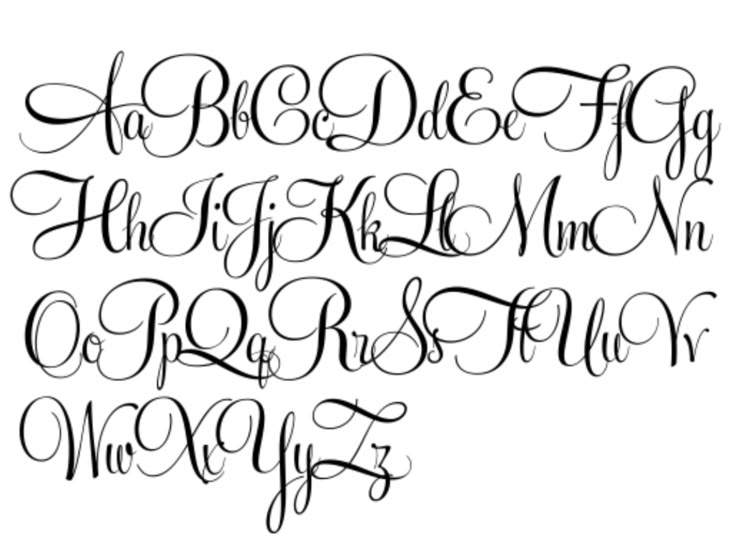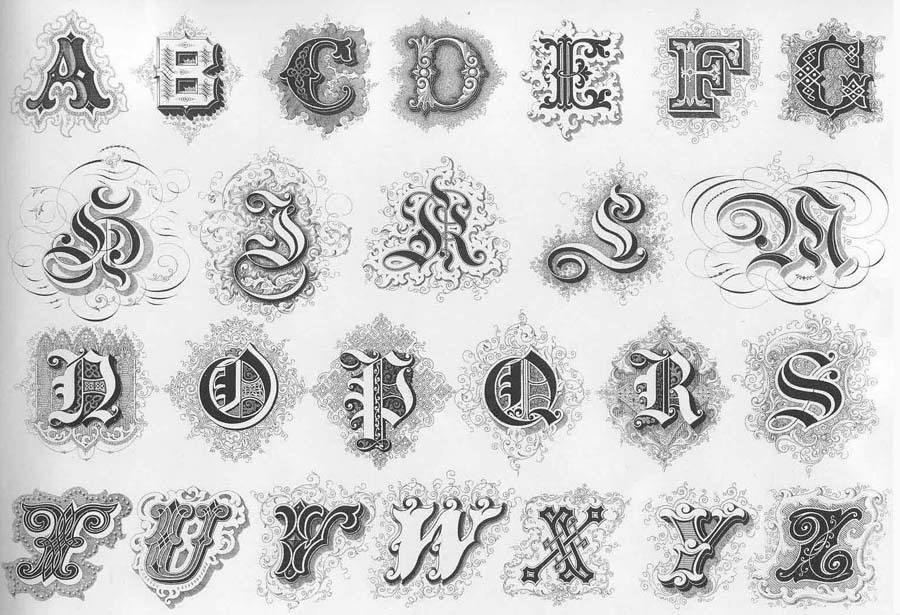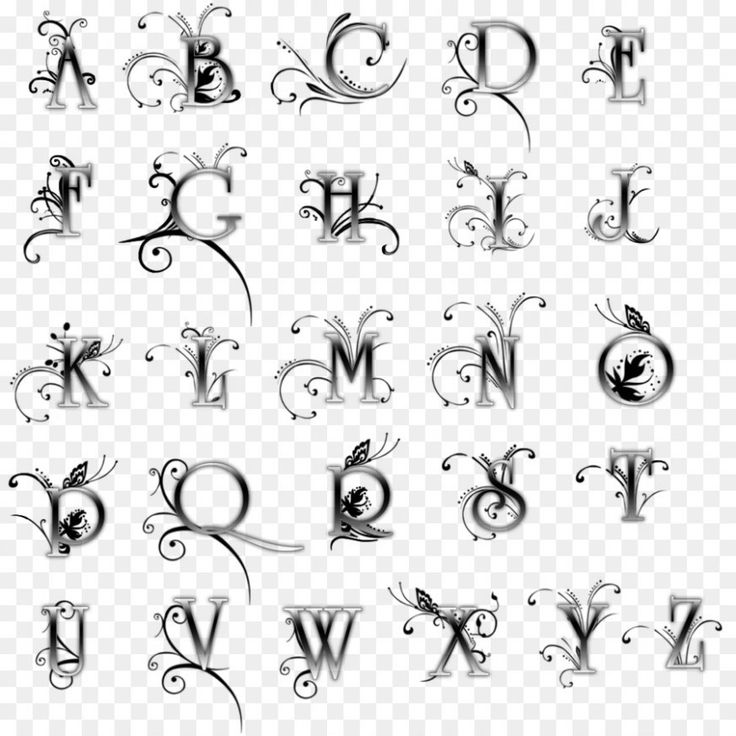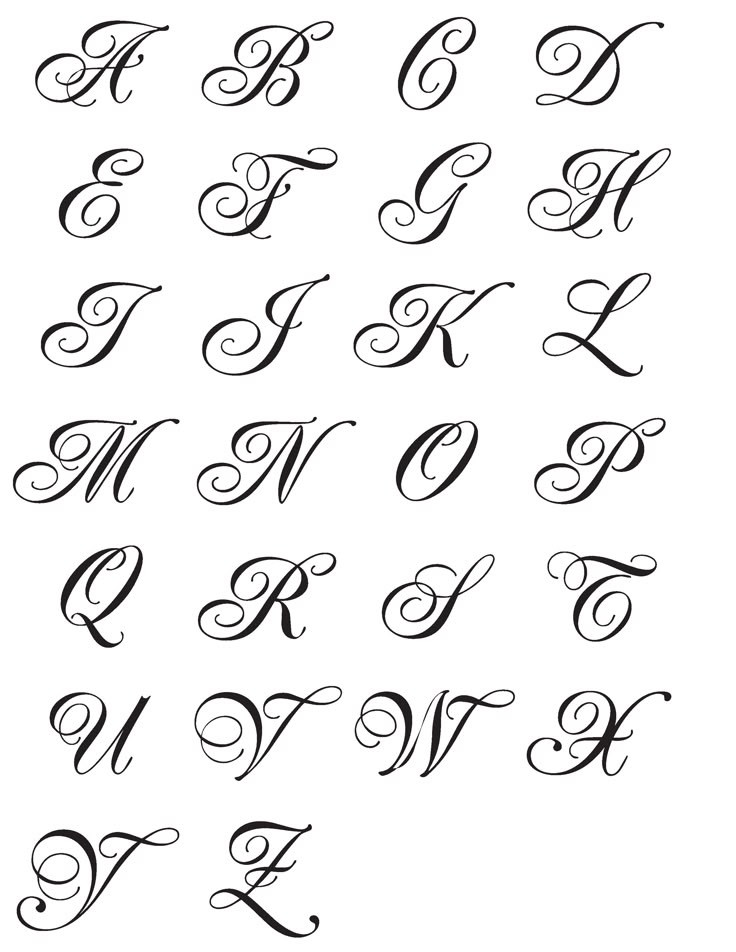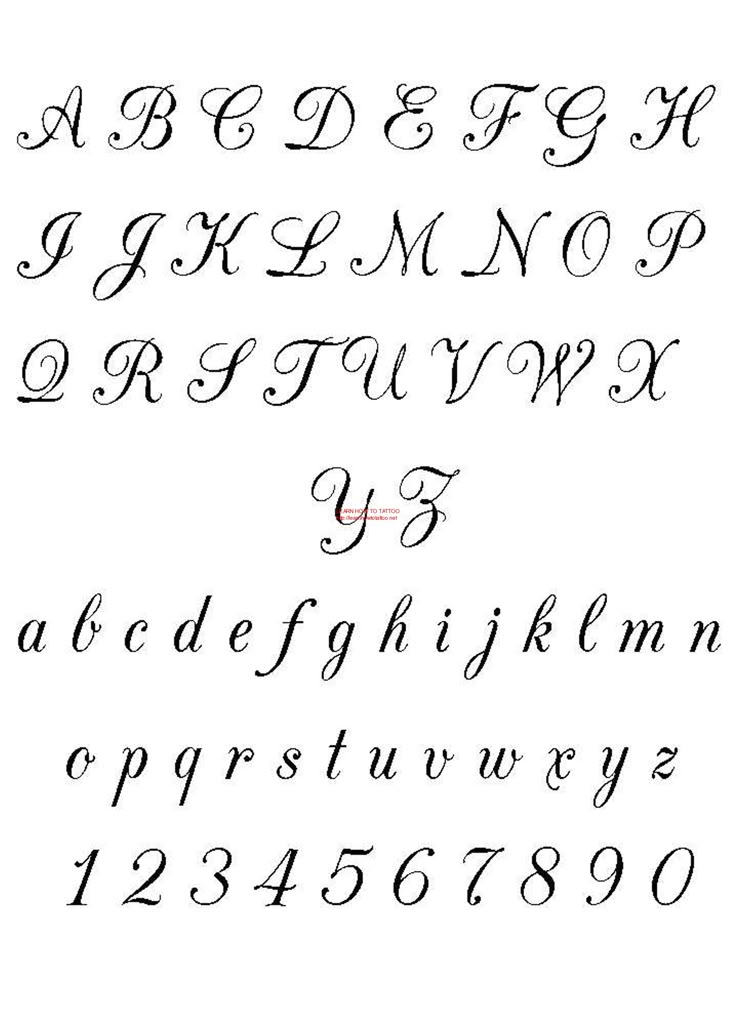
About Tattoo Fonts
Tattoo fonts can be used to preview and decide your text-based tattoos. Pure text tattoos become more and more trendy these days since more and more people choose words, names, short quotes and meaningful sayings to express themselves through their tattoos.
If you have already decided what to tattoo on your body, the next important thing is to decide what kind of lettering style you would like to use for your tattoo. Nobody would like their tattoo looks dull and unattractive, so you should do some research and choose your tattoo font or a tattoo lettering style that will give more color and personality. The most popular fonts for tattoos are script fonts, which usually look personal and unique, such as calligraphy and handwriting . are also used a lot in tattoo designs because they have a distinguished look and evoke some medieval atmosphere. Other popular fonts used in tattoos include: Celtic fonts , graffiti fonts , blade fonts etc.
Одним из самых распространенных стилей тату-индустрии является нанесение какого-либо текста для выполнения татуировки в итоге.
Выбор текста – вопрос непростой, но еще более сложным будет выбор самого шрифта. Учитывая целое море вариантов, а также индивидуальный подход мастера к каждому, можно долго рассуждать о конкретных типах тату.
Стиль шрифта
Размер шрифта
Чтобы определиться с размером шрифта нужно определить точное размещение текста.
Расположив его, можно представить другие варианты размеров – ширины и длины каждой буквы. Текст может состоять как со строчных буков, так и начинаться с заглавной, выделяя имя или город, страну.
Цвет надписи
Если Вы рассмотрели тату шрифты и определились с вариантом, а также уверены в тематике надписи, можно рассмотреть палитру цветов. Возможно, наилучшим вариантом будет черно-белая татуировка или же актуальнее будет сделать тату в ярких цветах. Можно сделать несколько цветов, комбинируя их:
- Сделать яркую обводку.
- Добавить цветную тень.
- Заполнение букв может быть с цветовыми переходами.
Стиль самого тату может быть как минимализм, так и готика или графика. Вы сами выбираете наилучший стиль для своего тату, однако совет мастера всегда будет полезен. Рассмотрите тату шрифты у нас, подумайте об оформлении, выберите несколько вариантов и продумайте заранее все детали.
Язык надписи
Немаловажным фактором является выбранный язык для татуировки. Исходя из выбора, нужно прикинуть шрифт, так как не каждый из них хорошо смотрится на том или другом языке. Для понимания онлайн пропишите надпись, которую собираетесь набивать, чтобы рассмотреть все преимущества и недостатки того или другого шрифта.
Desirable Calligraphy
Tribal Font
Young Heart Typeface
Inked Skin
Caroollina
Secret Society
Starella Tattoo
Mortal Tattoo Font
Storm Fighter
Шрифт Bad Sailor
Наборы шрифтов S&S GreyHood
Эти кривые могут помочь вам подчеркнуть ваш дизайн.